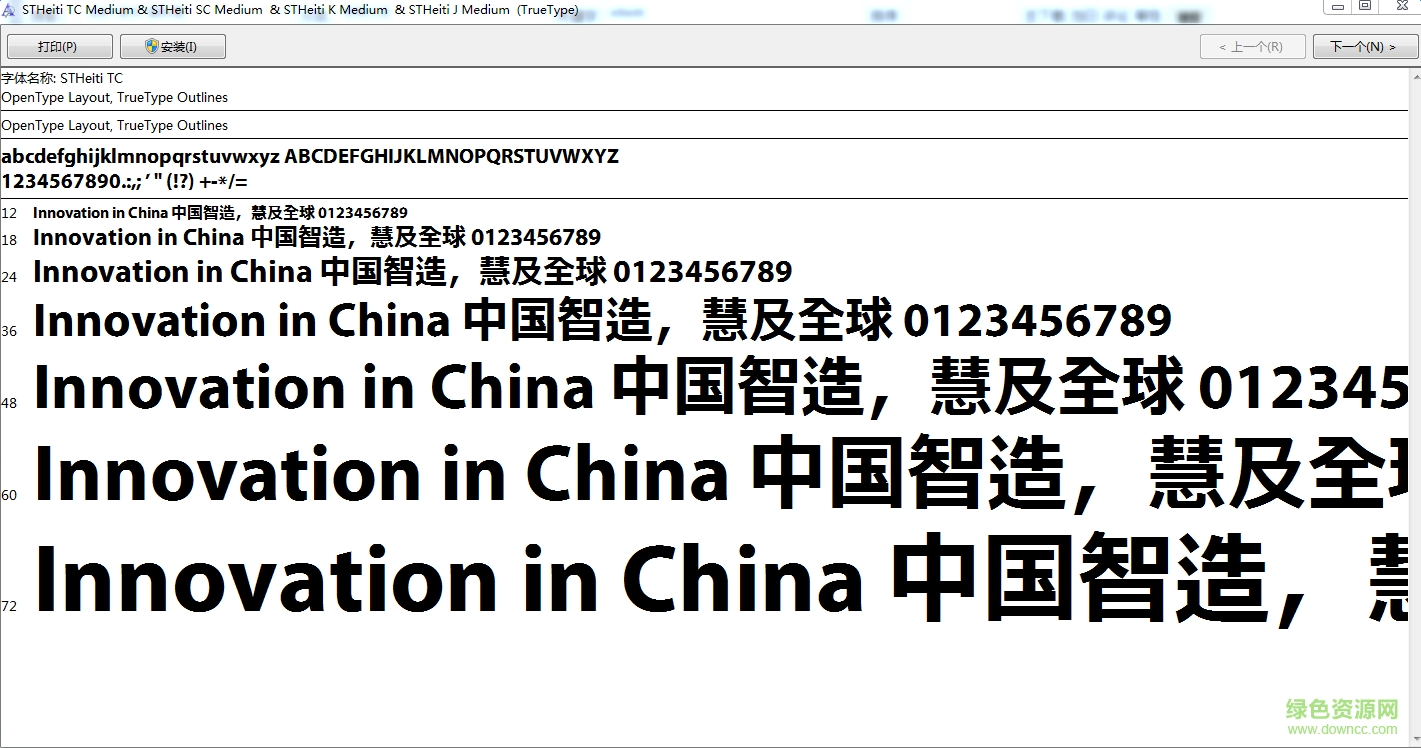
stheiti tc medium字體
stheititc medium字體是一款ttf格式的黑體字,該字體粗黑厚重,字形端正,結(jié)構(gòu)嚴謹,正氣十足,可應(yīng)用在影視印刷、廣告設(shè)計、產(chǎn)品包裝等多個領(lǐng)域,有需要者歡迎在綠色資源網(wǎng)下載!